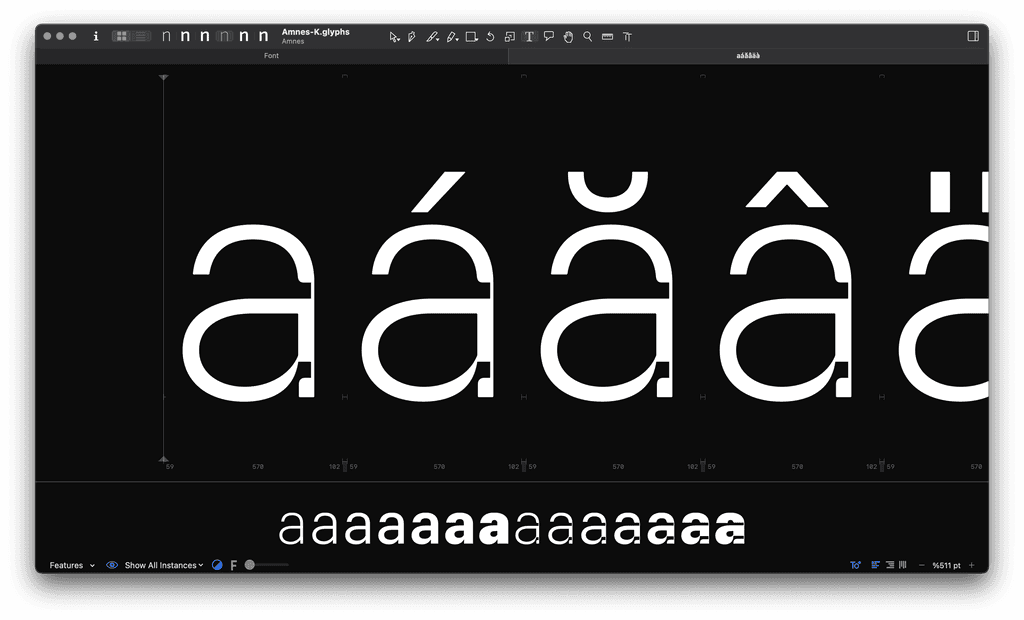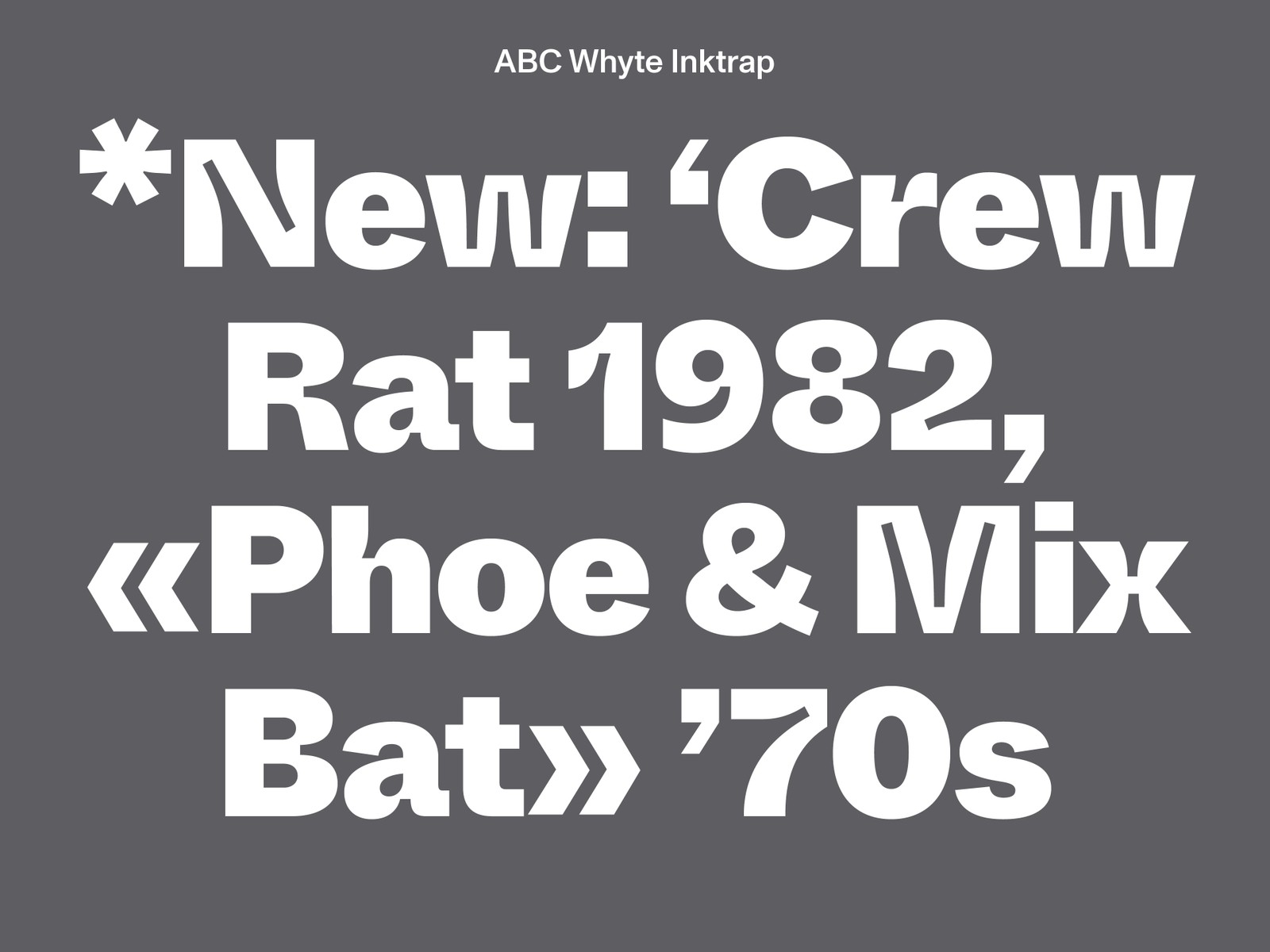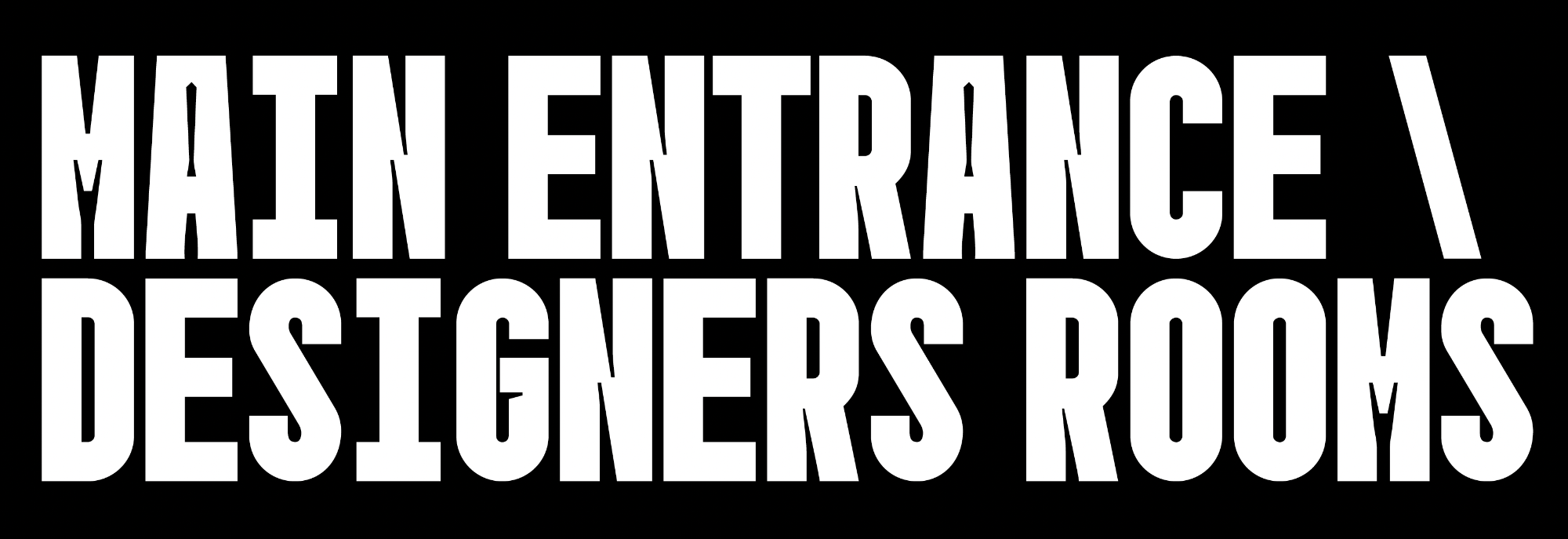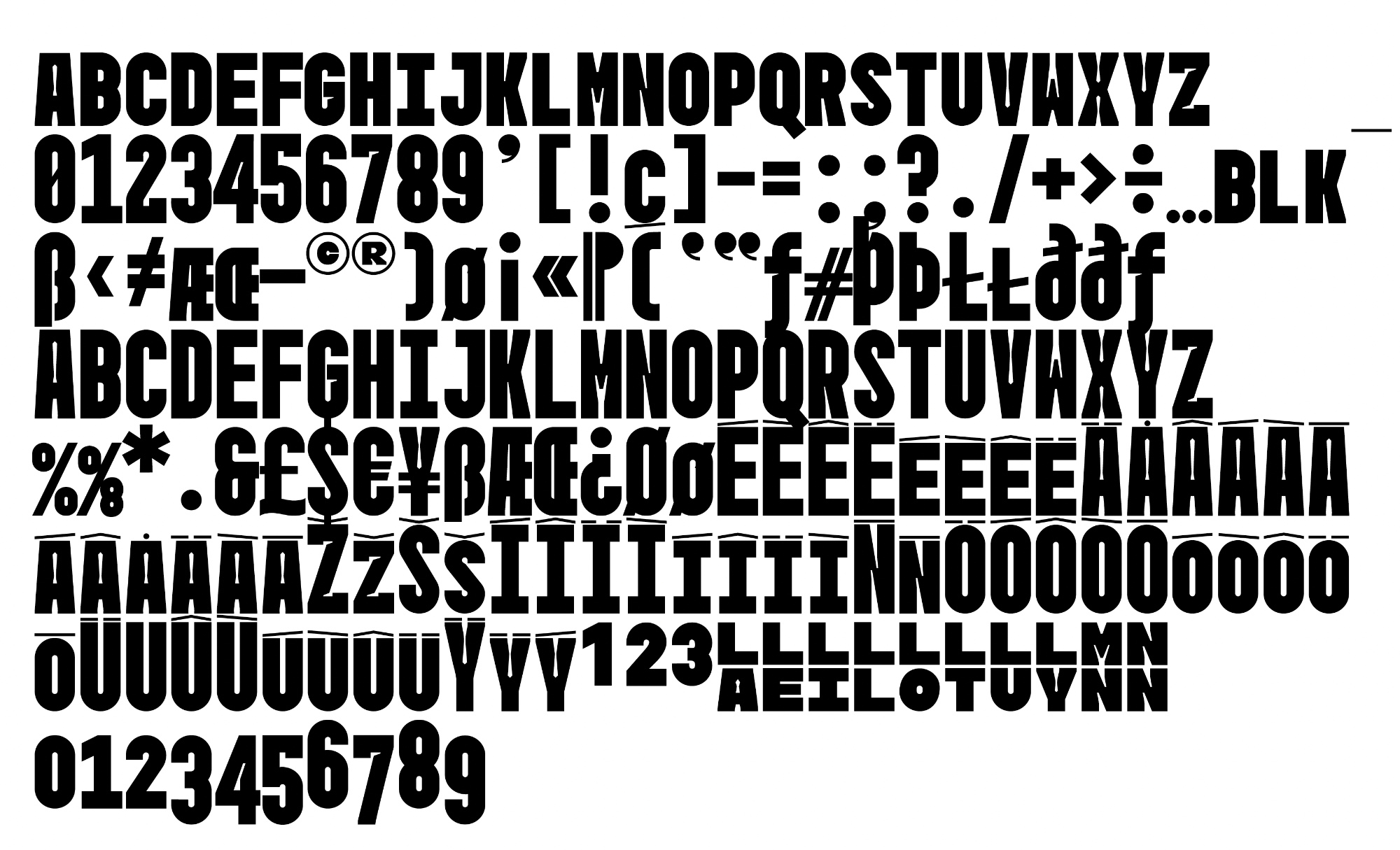
Betonte Tintenfallen ...
Die Raum gefällt mir. Aber – sind das noch Tintenfallen? Es ist doch mehr Schmuck als funktionelle Aussparung.
Bei ‹V›, ‹M›, ‹d›, ‹r› und ähnlichen könnte man ja noch von zu gr0ß geratenen Ink Traps reden. Bei ‹e›, ‹o›, ‹c› und vor allem beim ‹l› muss an den ausgesparten Stellen doch gar keiner überschüssigen Tinte Platz geschaffen werden.
Trotzdem schön!
Bei der Lipa sind die Fallen an den richtigen Stellen (überall, wo etwas zulaufen könnte) angebracht. Bei der Live Grotesk FM sind die Fallen Schmuck, was man schön daran erkennen kann, dass zB die Kreuzung des T-Strichs mit dem Stamm nur auf einer Seite gesichert ist; an den anderen drei Einmündungen muss sich die Tinte gefälligst zusammenreißen. :-)
ABC Whyte
AF Mona Mono
Amnes
Amplitude
Atipla ND
Avancar
Bauziet
BC Civitas
Bell Centennial
Bell Gothic
Biwa Agate
BN Crocker
Borna
Brevier
Degular
DINfun Pro Inktrap
FF Hydra
Fritzi
Gemeli Micro
Ginka
Gnarly
Groove
GT Eesti
GT Flexa
GT Zirkon
Heltar
Holand Century
Ink Trap Sans
JT Oliver
Lipa Agate
Live Grotesk FM
Maax Micro
Magnet
McQueen
Minotaur Beef
Nebula
Neue Machina
Noi Grotesk
NT-Voice
Oddval
Plastique
Poly Sans
Polysans
Radix
Raum
Reaktif
Rhosyn
Shaunte Inktrap
Sligoil
Tabac Micro
Trench Sans
Yanice
Zimula